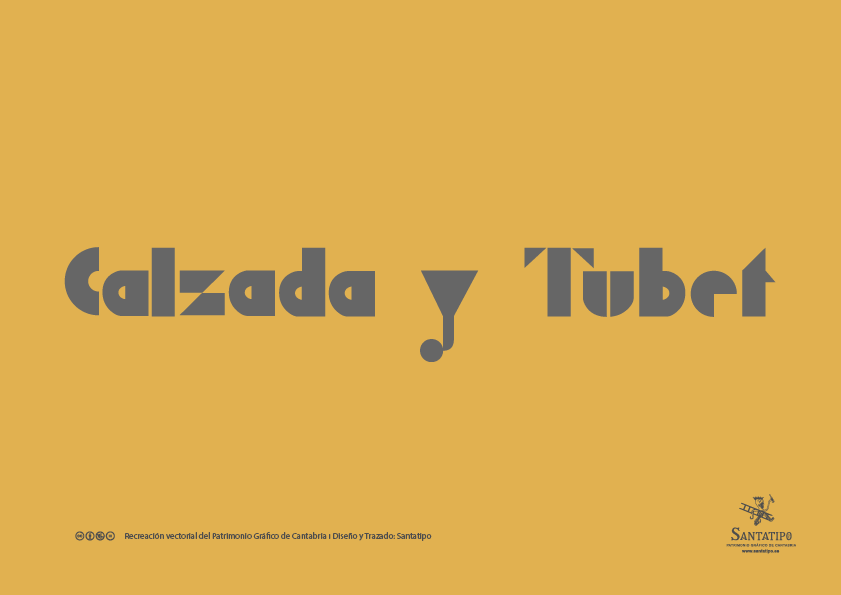
Calzada y Tubet
Una maravilla de imprenta en la que se pueden apreciar todos los detalles in situ de la impresión, así como el diseño de esa tipografía geométrica. Ojo al detalle del número de teléfono.